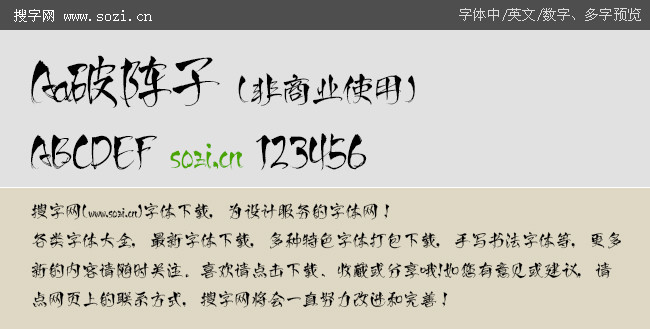
Aa破陣子
搜字網(wǎng)給大家提供一款Aa破陣子(非商業(yè)使用)中文字體下載,該字體是一款手寫風格的毛筆藝術字體,字型非常的瀟灑自由,沒有連筆畫,橫豎撇捺都有固定的規(guī)律,工整簡潔,具有強烈的視覺沖擊力。適用于平面宣傳設計、網(wǎng)頁設計、海報設計等應用(此字體為個人非商用版,商用可以聯(lián)系QQ:1006760504)。